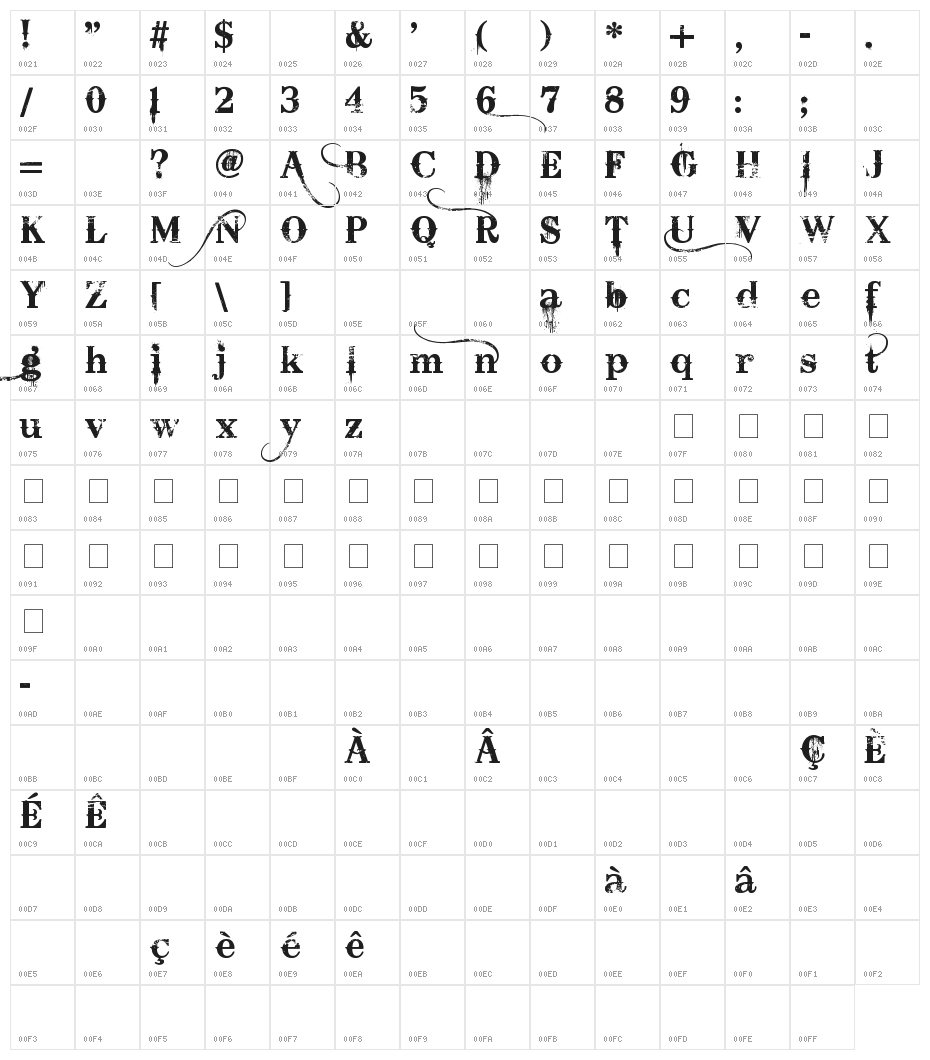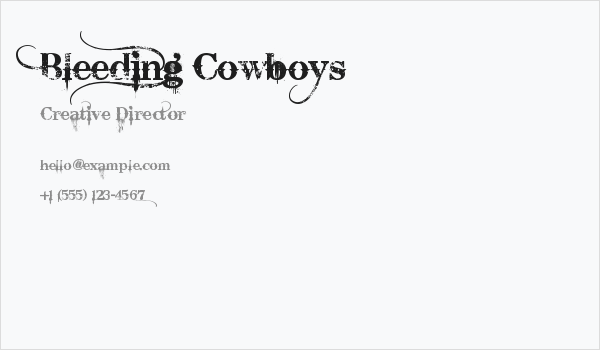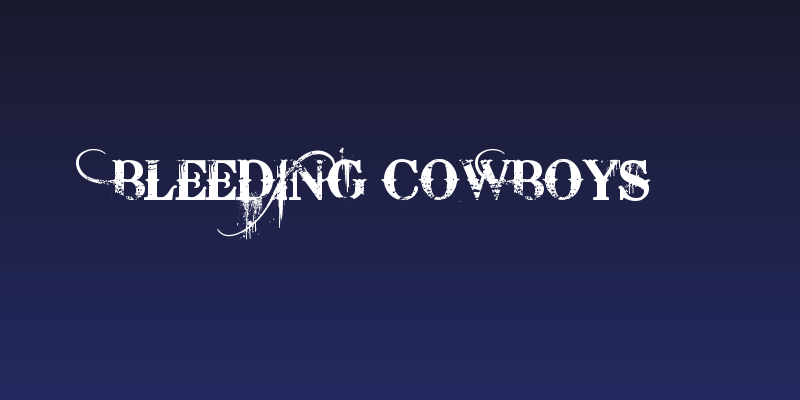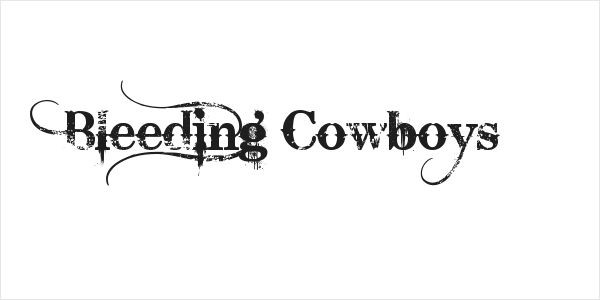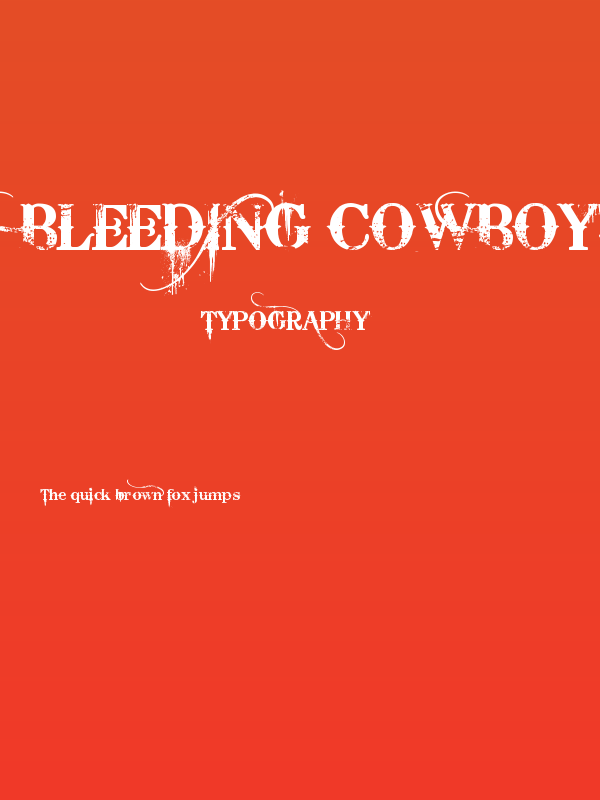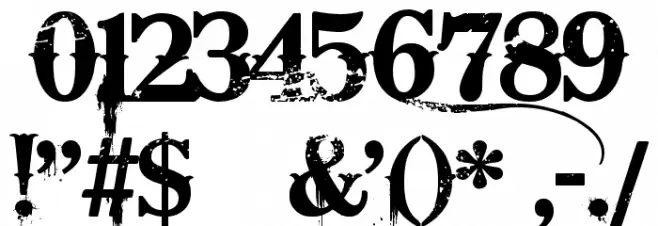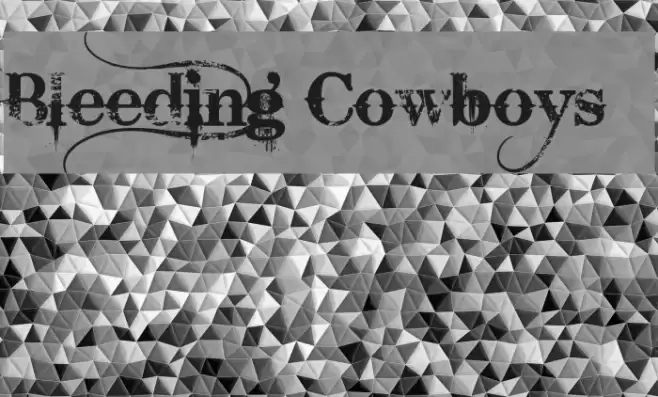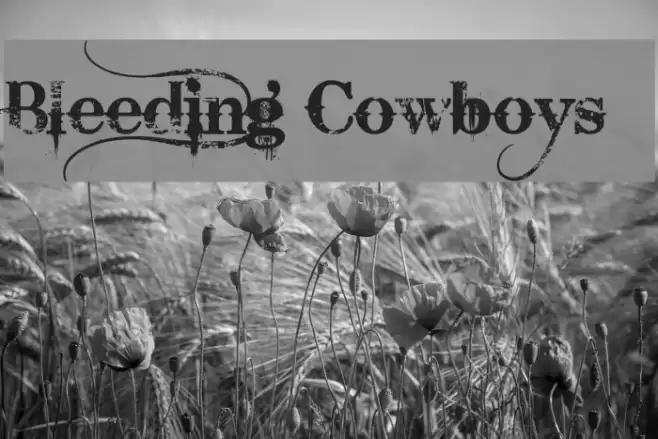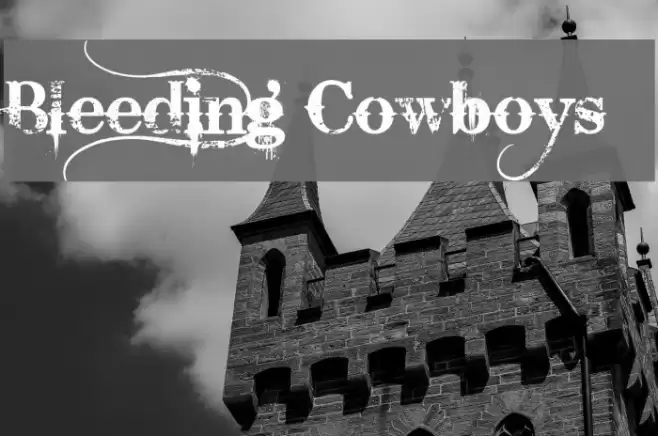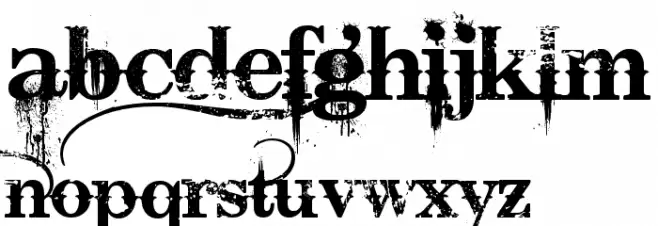
Bleeding Cowboys Font
✎ Western
| Proiecte propuse | Ideal for album covers, posters, branding for edgy or vintage-themed products, and any design needing a bold, artistic touch. |